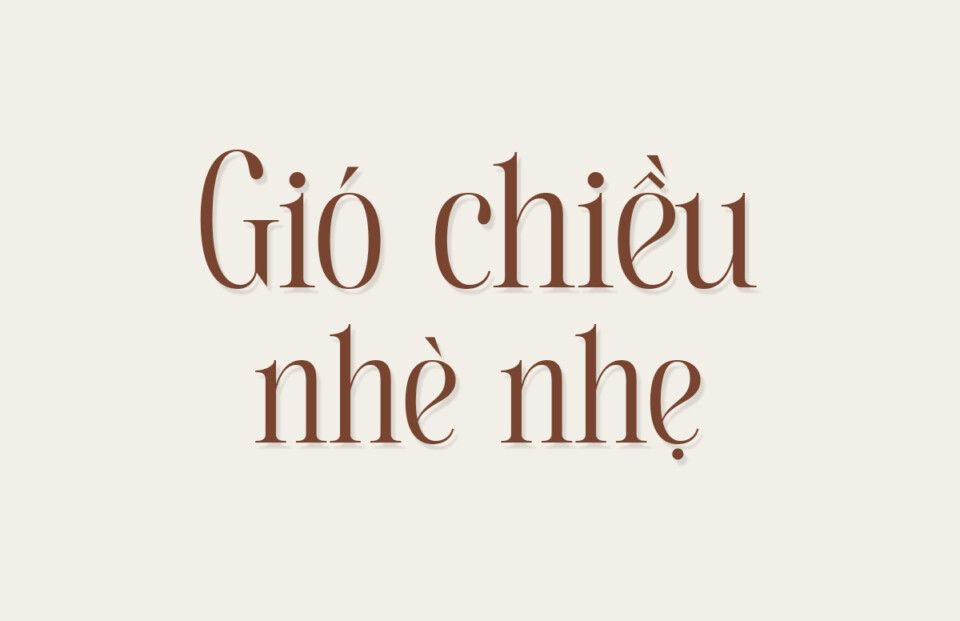
Font Việt hóa 1FTV VIP Mirosela là mẫu chữ mang phong cách thanh lịch, mềm mại và giàu tính nghệ thuật, giúp nhà thiết kế, người sáng tạo nội dung và chủ thương hiệu dễ dàng ứng dụng font vào ấn phẩm truyền thông, nhận diện thương hiệu, thiệp mời hoặc nội dung mạng xã hội.
Không chỉ tạo cảm giác sang trọng, Mirosela còn sở hữu đường nét duyên dáng, giúp tiêu đề và thông điệp trở nên nổi bật mà không quá nặng nề. Đây là lựa chọn đáng cân nhắc nếu bạn đang tìm kiếm một font chữ Việt hóa có tính thẩm mỹ cao, dễ phối hợp và phù hợp với nhiều chủ đề sáng tạo.
Font Việt hóa 1FTV VIP Mirosela thanh lịch dành cho thiết kế sáng tạo
Font Việt hóa 1FTV VIP Mirosela gây ấn tượng bởi vẻ đẹp tinh tế, giàu cảm xúc và khả năng truyền tải thông điệp bằng hình thức trực quan cuốn hút. Kiểu chữ phù hợp với những thiết kế hướng đến sự nữ tính, lãng mạn, cao cấp hoặc mang hơi thở thủ công. Từ các tiêu đề ngắn, tên thương hiệu cho đến câu trích dẫn giàu cảm xúc, Mirosela đều có thể góp phần nâng cao giá trị thẩm mỹ của bố cục.
Điểm đáng chú ý của phiên bản Việt hóa là khả năng hiển thị đầy đủ các ký tự và dấu tiếng Việt phổ biến. Người dùng có thể soạn nội dung tự nhiên hơn, hạn chế tình trạng thiếu dấu, lỗi ký tự hoặc phải thay thế chữ thủ công. Nhờ đó, quá trình thiết kế trở nên nhanh chóng, đồng nhất và chuyên nghiệp hơn, đặc biệt khi làm việc với các dự án có nhiều nội dung tiếng Việt.
Hỗ trợ tiếng Việt đầy đủ và thuận tiện
Một trong những ưu điểm quan trọng của Font Việt hóa 1FTV VIP Mirosela là khả năng hỗ trợ hệ thống dấu tiếng Việt. Các ký tự như ă, â, ê, ô, ơ, ư, đ cùng những tổ hợp dấu thanh được xử lý để phù hợp với đặc điểm tạo hình của font. Điều này giúp nội dung giữ được phong cách thẩm mỹ thống nhất giữa chữ cái cơ bản và chữ có dấu.
Khả năng gõ tiếng Việt thuận tiện đặc biệt hữu ích đối với người làm thiết kế quảng cáo, quản trị mạng xã hội, sáng tạo nội dung và xây dựng thương hiệu tại thị trường Việt Nam. Thay vì phải chỉnh sửa từng dấu hoặc chuyển đổi qua nhiều công cụ, người dùng có thể tập trung vào ý tưởng, bố cục và thông điệp chính của sản phẩm.
Phong cách mềm mại, thanh lịch và giàu cảm xúc
Mirosela sở hữu đường nét uyển chuyển, tạo cảm giác nhẹ nhàng nhưng vẫn có cá tính. Phong cách này giúp font trở thành điểm nhấn phù hợp cho các thiết kế liên quan đến thời trang, mỹ phẩm, làm đẹp, hoa cưới, trang sức, nhiếp ảnh, dịch vụ cưới hỏi, quà tặng và sản phẩm thủ công. Khi được sử dụng đúng kích thước và khoảng cách, kiểu chữ có thể mang lại cảm giác tinh tế, gần gũi và cao cấp.
Đặc trưng giàu cảm xúc của font còn phù hợp với các câu trích dẫn, lời chúc, tên riêng, tiêu đề bộ sưu tập hoặc thông điệp ngắn. Người thiết kế có thể kết hợp Mirosela với một font không chân đơn giản để tạo sự cân bằng: Mirosela đảm nhiệm phần tiêu đề nổi bật, trong khi font phụ trình bày nội dung dài và thông tin chi tiết.
Ứng dụng linh hoạt trong nhiều sản phẩm thiết kế
Font Việt hóa 1FTV VIP Mirosela có thể được sử dụng trong nhiều loại ấn phẩm kỹ thuật số và in ấn. Tùy theo mục đích, người dùng có thể điều chỉnh kích thước, màu sắc, độ tương phản và cách sắp xếp để tạo ra phong cách riêng. Một số ứng dụng nổi bật gồm:
- Thiết kế logo chữ, tên thương hiệu, nhãn sản phẩm và biểu trưng cá nhân.
- Thiết kế thiệp cưới, thiệp mời, thiệp chúc mừng, menu và bảng tên sự kiện.
- Tạo tiêu đề poster, banner, ảnh quảng cáo, bài đăng Facebook và Instagram.
- Trang trí bao bì mỹ phẩm, thời trang, nến thơm, hoa, đồ thủ công và quà tặng.
- Trình bày câu trích dẫn, ảnh bìa, watermark, portfolio và ấn phẩm nhiếp ảnh.
Để đạt hiệu quả tốt, Mirosela nên được ưu tiên cho tiêu đề, tên gọi hoặc các đoạn nội dung ngắn. Với phần văn bản dài, người dùng nên chọn một font phụ có khả năng đọc tốt và kiểu dáng tối giản. Cách kết hợp này vừa giúp thiết kế có điểm nhấn, vừa bảo đảm người xem tiếp nhận thông tin rõ ràng.
Dễ phối hợp trong hệ thống nhận diện thương hiệu
Một kiểu chữ có cá tính rõ ràng có thể góp phần định hình cảm nhận của khách hàng về thương hiệu. Với nét chữ mềm mại và thanh lịch, Font Việt hóa 1FTV VIP Mirosela phù hợp với những thương hiệu muốn xây dựng hình ảnh tinh tế, thân thiện, lãng mạn hoặc giàu chất nghệ thuật. Font có thể xuất hiện trên logo, slogan, bao bì, danh thiếp và nội dung truyền thông để tăng tính nhất quán.
Khi xây dựng bộ nhận diện, người dùng nên xác định rõ vai trò của Mirosela trong hệ thống chữ. Font có thể được dùng làm kiểu chữ tạo điểm nhấn, trong khi một kiểu sans serif hoặc serif dễ đọc được sử dụng cho phần thông tin. Việc giới hạn số lượng font và duy trì quy tắc sử dụng thống nhất sẽ giúp thương hiệu trông chuyên nghiệp hơn trên cả nền tảng trực tuyến lẫn ấn phẩm in.
phù hợp với nhiều dự án thiết kế cần tạo dấu ấn riêng. Phiên bản Việt hóa hỗ trợ nhập liệu tiếng Việt thuận tiện,